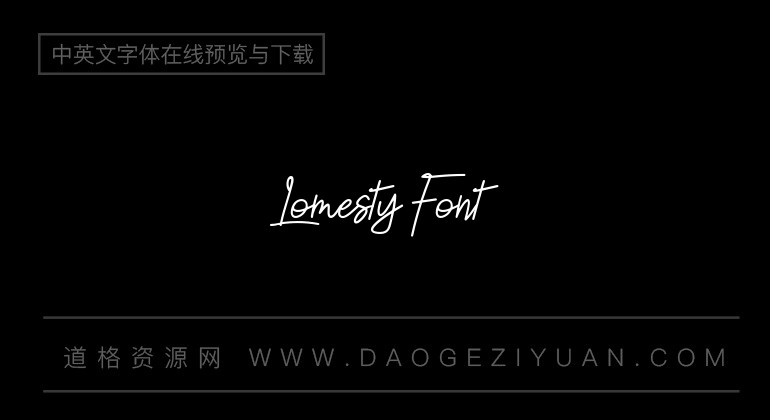
Lomesty Font
Lomesty Font 是一种现代、简洁、流畅的字体,由设计师Maulana Creative于2019年创作并发布。该字体既具有独特的个性,又易于阅读,非常适合用于各种设计项目中,例如海报、名片、标志、包装等。 Lomesty Font具有粗体和细体两种风格,它们都包含大写字母、小写字母、数字和标点符号。该字体还支持多种语言,包括英语、法语、西班牙语、德语、意大利语等,使得它非常适合在全球范围内使用。 总的来说,Lomesty Font是一种非常优秀的字体,它的简洁性和现代感使得它在许多设计项目中都能起到非常好的作用,是一个值得尝试的字体。
Lomesty Font是一款非常不错的手写艺术字体,具有很好的视觉感,适合于文化类的宣传设计、商业类品牌的广告和产品包装设计以及个性化文字排版等较多场景。